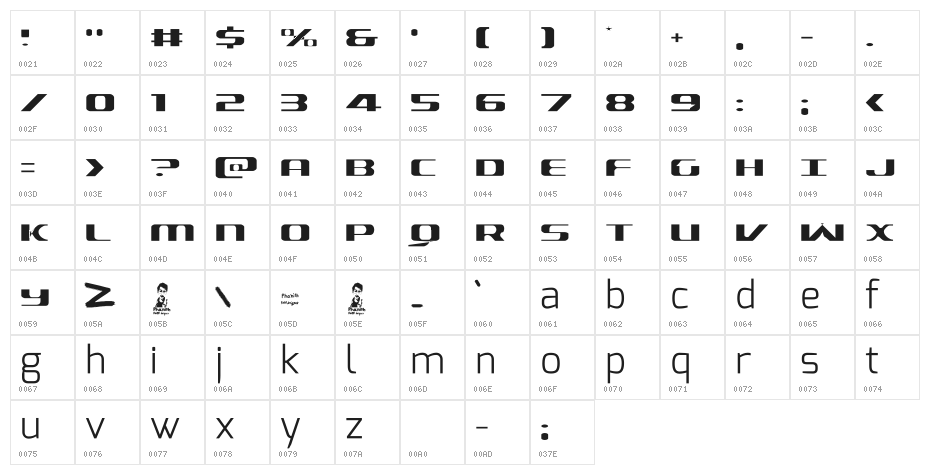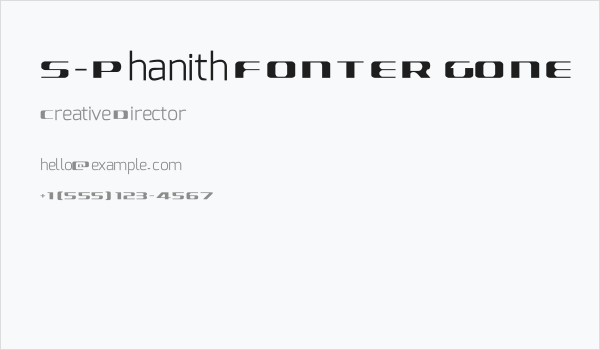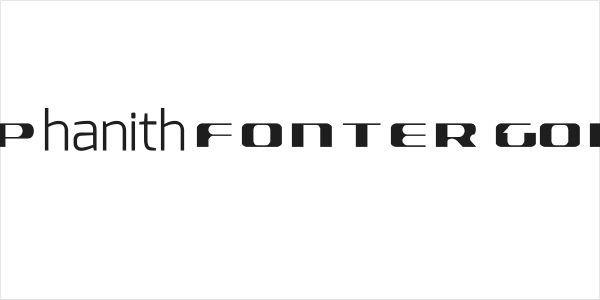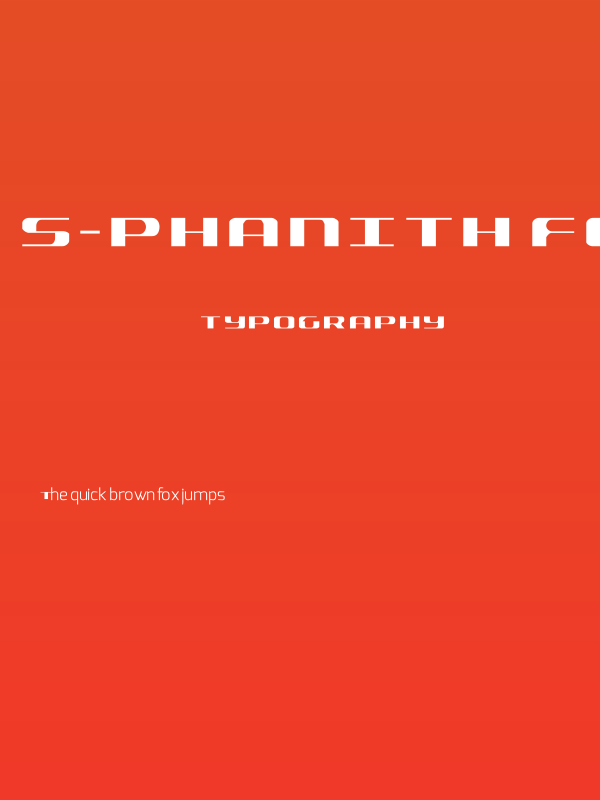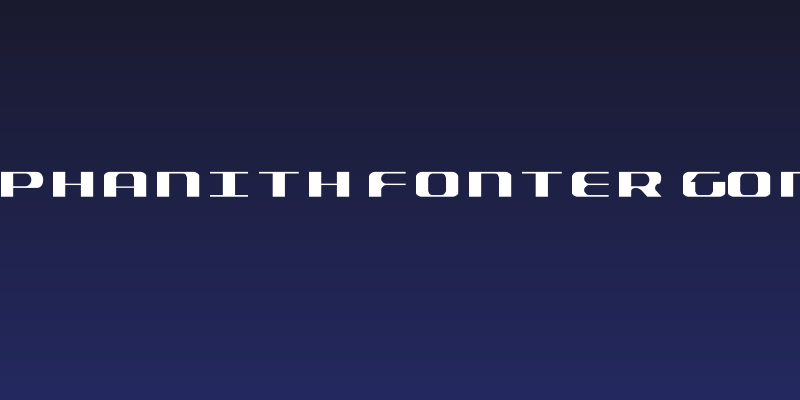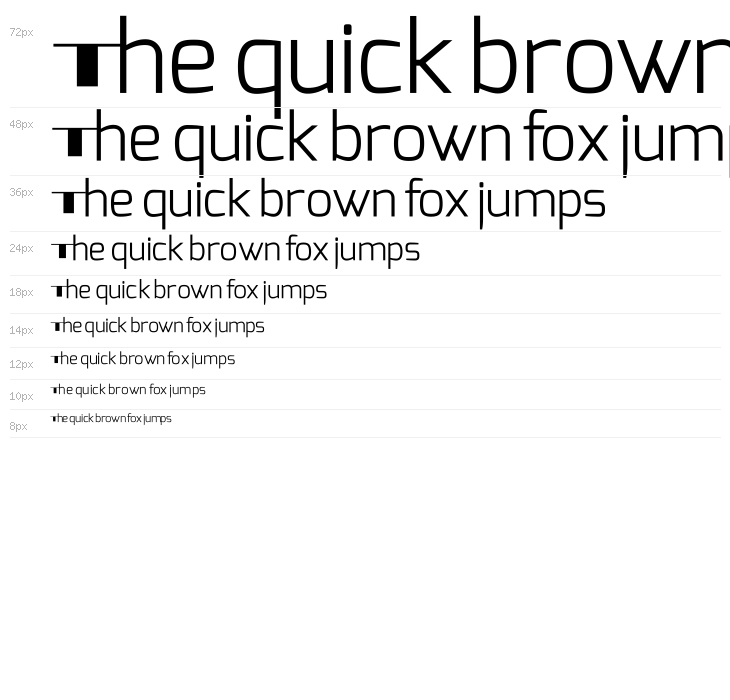
S-Phanith FONTER GONE Font
| Progetti proposti | Ideal for tech branding, sci-fi themes, modern advertising, and innovative design projects. |
S-Phanith FONTER GONE